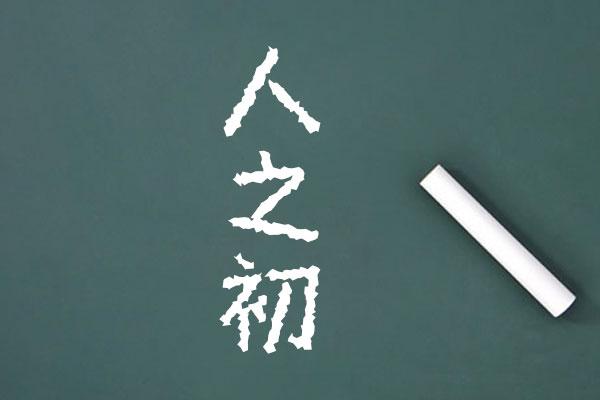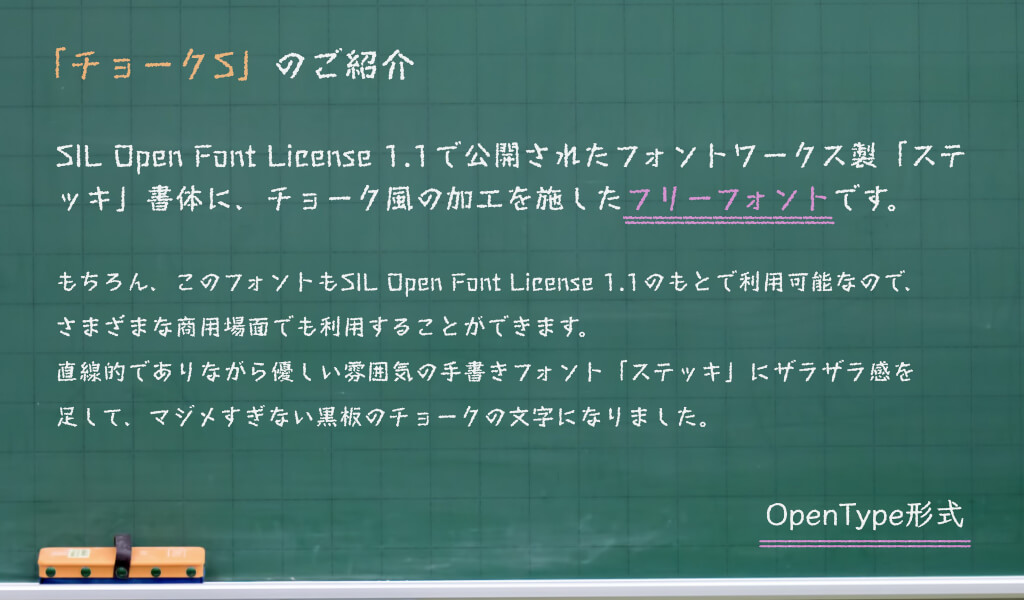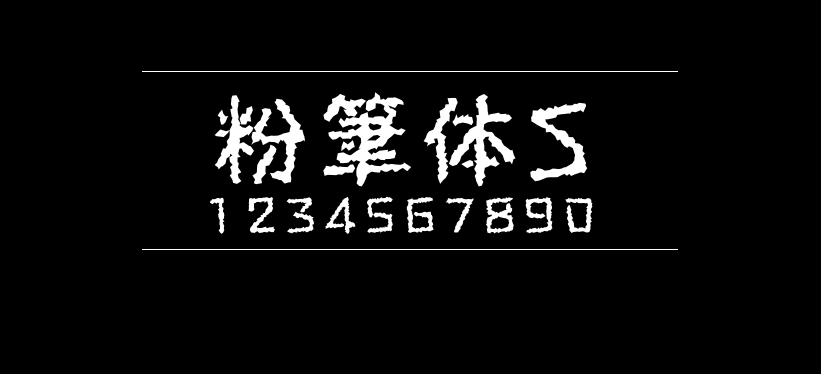
粉笔体S
粉笔体S(Chalk-S JP / チョークS)是基于Fontworks系列的拐杖字体进行二次创作,给字体的边缘加上破损效果,让字体看起来像粉笔字一样。这款字体与自由君给大家介绍过的另一款的日系粉笔体相似,与之前的粉笔体相比,粉笔体S会显示得更粗,手写感更强烈。
由于粉笔体S是日本推出的一款字体,其繁体字支持得还不错,简体字形则存在缺字现象。